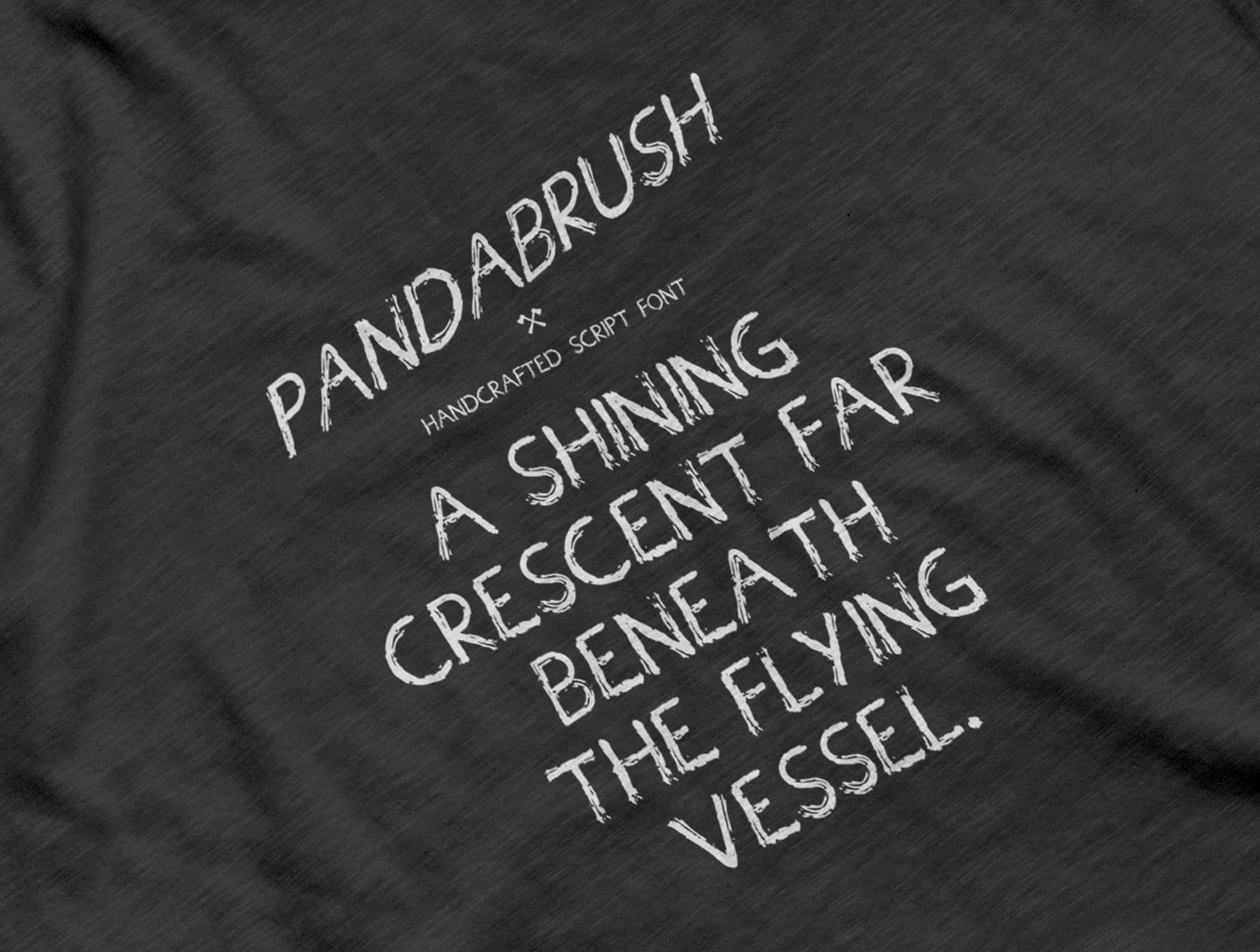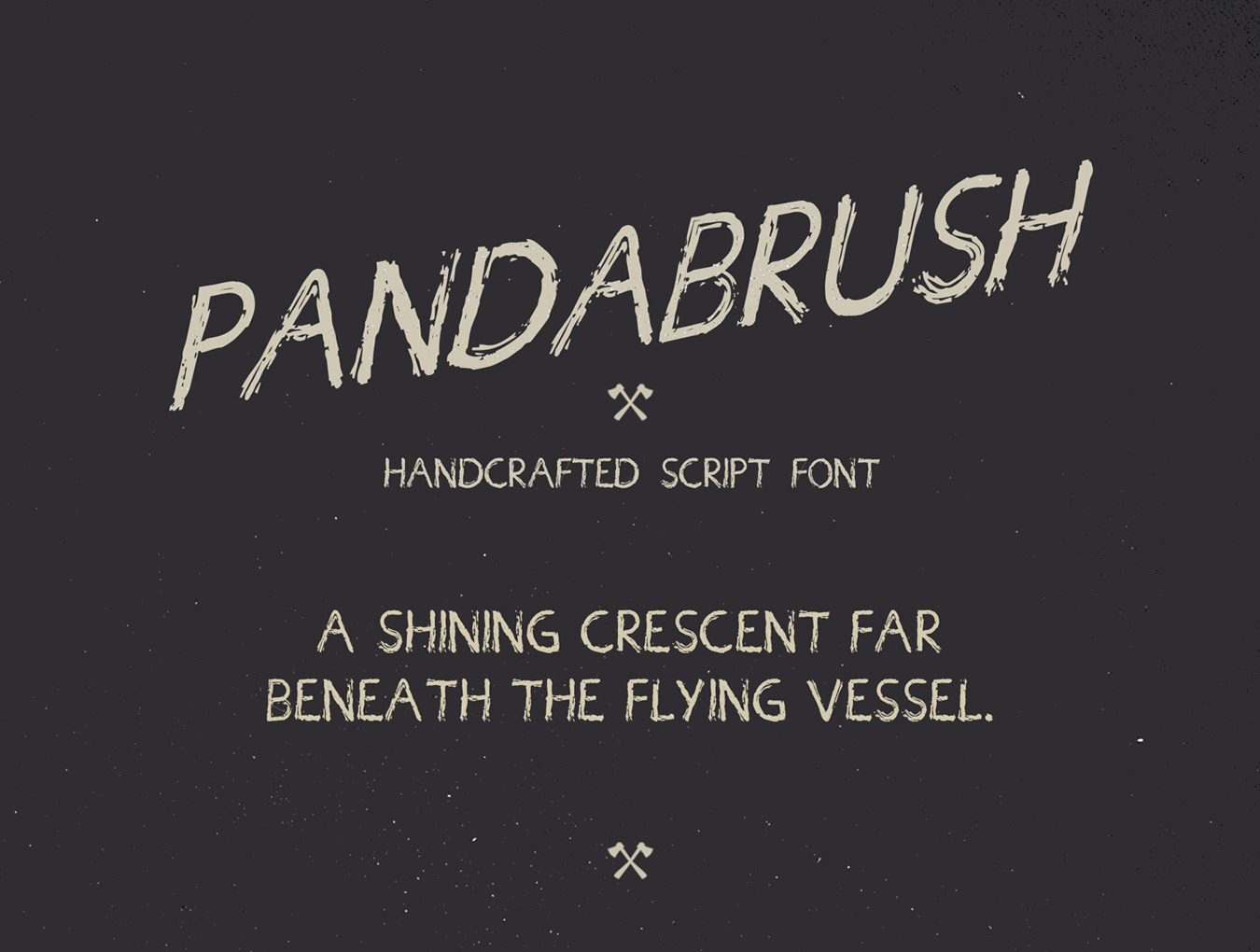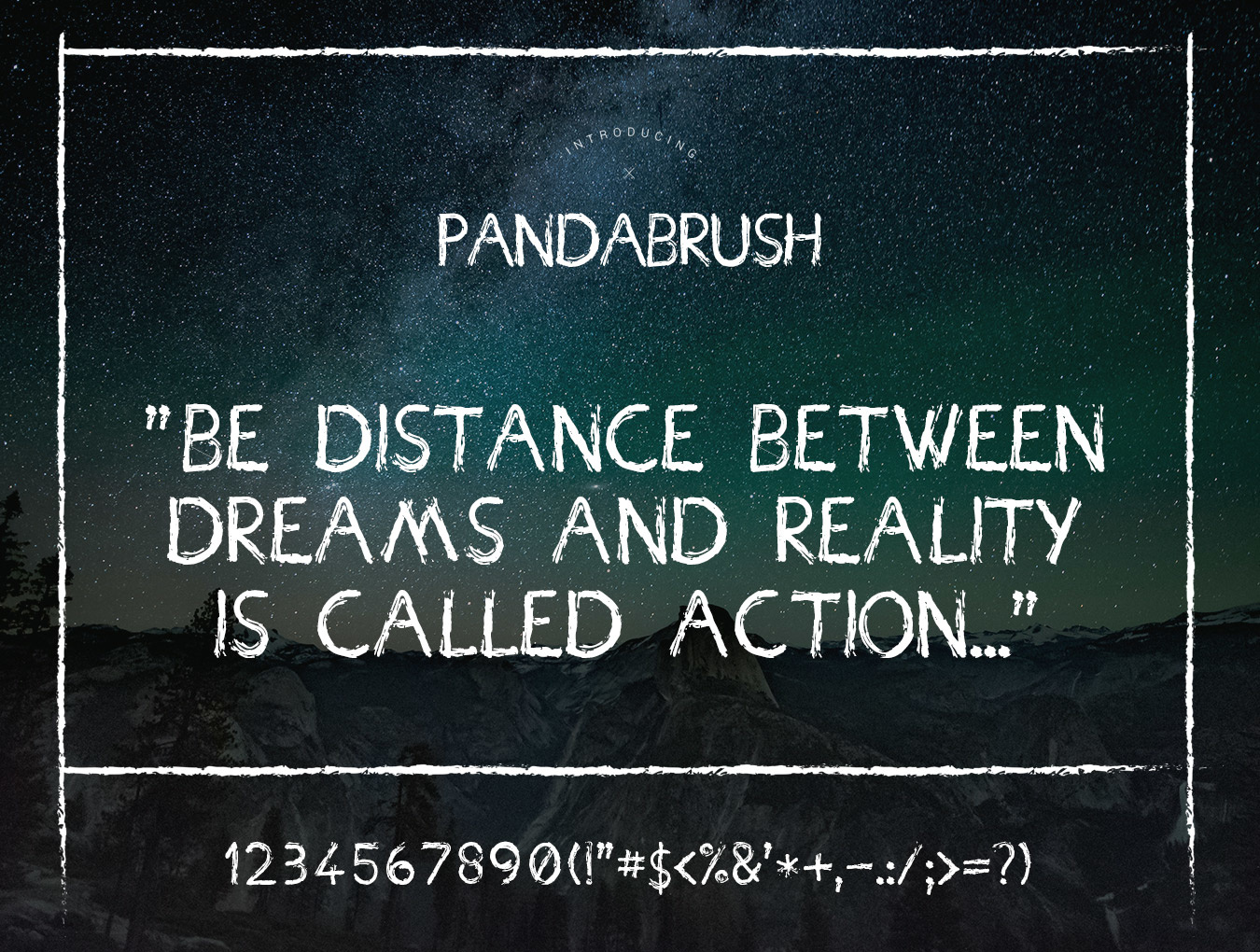
Pandabrush是一种手绘笔刷字体大写字母。,Pandabrush字体
Pandabrush is a hand-drawn brush font uppercase letters., Pandabrush Typeface
Pandabrush是一种手绘笔刷字体大写字母。它非常适合徽标,品牌,印刷项目和任何引人注目的标题。 Pandabrush包括大写字母,标点符号和数字。